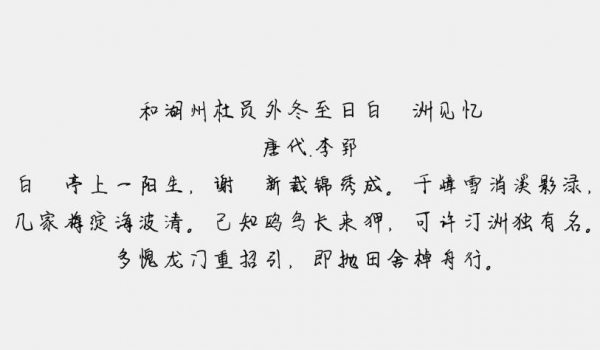
若梦体是一款十分靓丽的中文字体,同时也是由文道字库倾情发布的作品,字体字型书写的非常行云流水,连笔流畅,连笔流畅,适应于报纸和杂志和书籍中常用字体海报、个性促进品牌标志设计、字体设计、文本装潢、信息展示、篆刻制模英文、数据制作、装潢设计、视觉设计、字帖等一切合法应用场景,有喜欢的朋友可免费下载收藏。